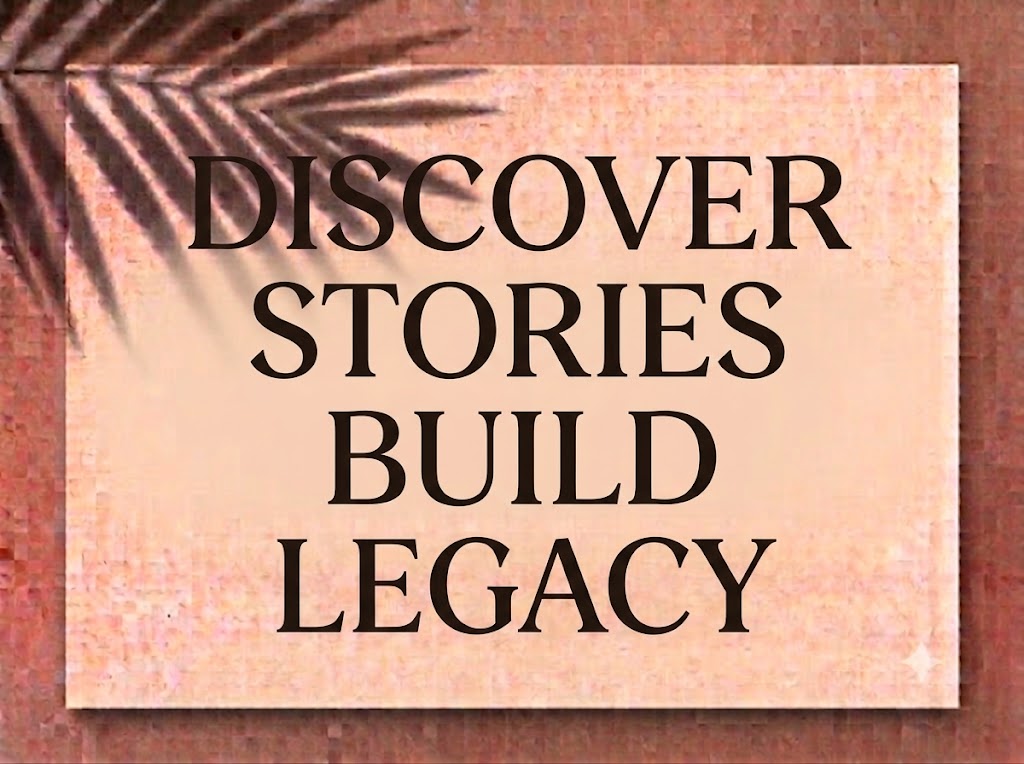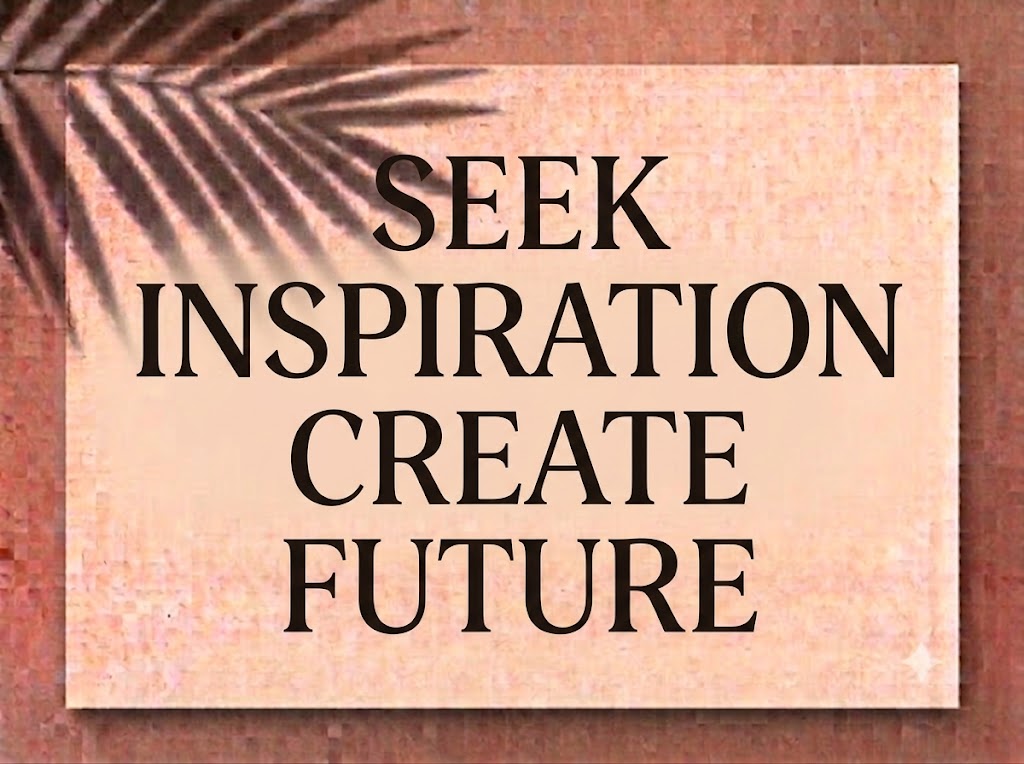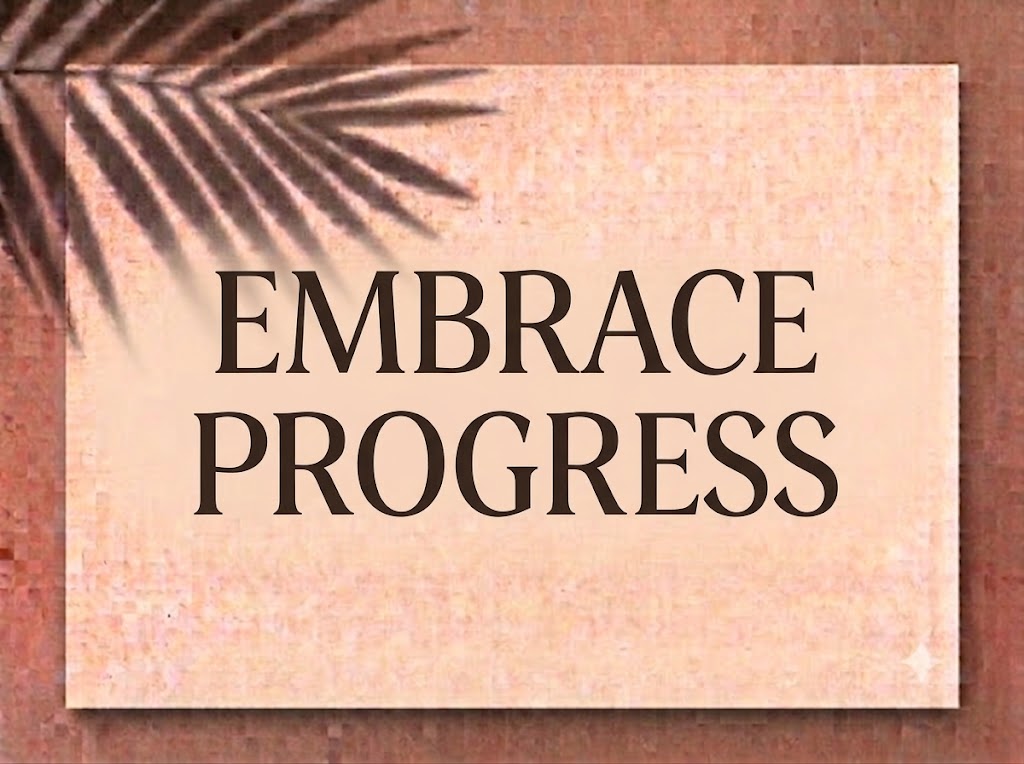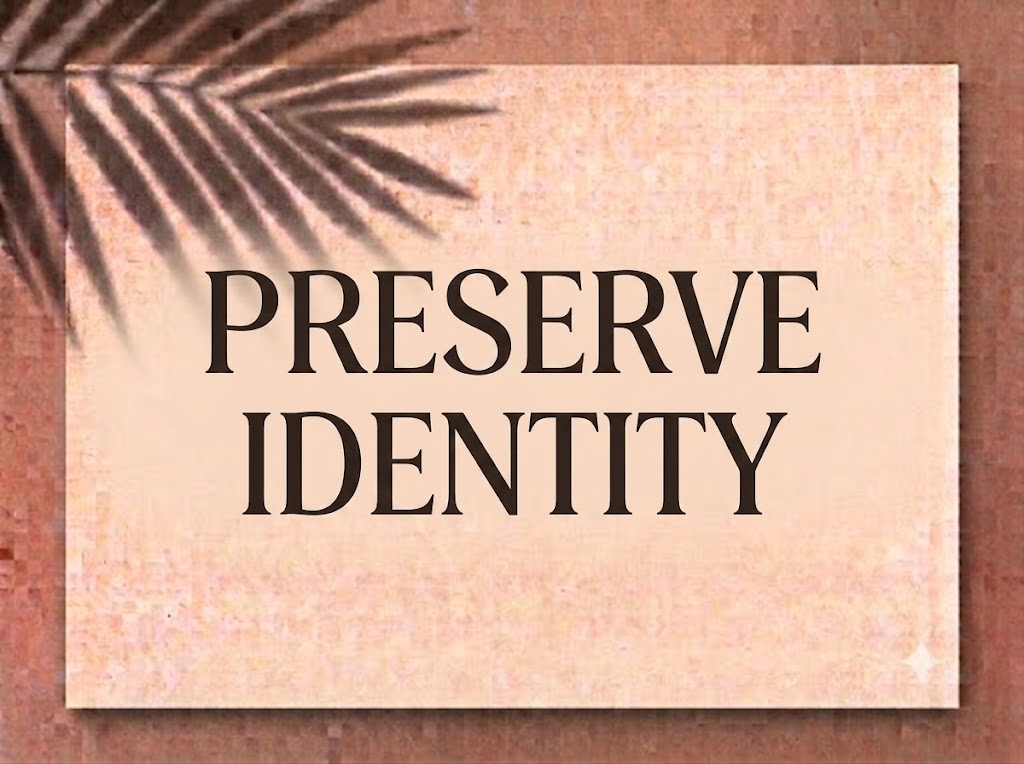
1FTV VIP Alverich
Trong ngành thiết kế đồ họa cao cấp, thời trang và sản xuất nội dung số, việc lựa chọn một phông chữ Serif vừa giữ được vẻ kiêu sa cổ điển vừa mang đường nét hiện đại là yếu tố quyết định giá trị thị giác. Một dòng tiêu đề được tạo hình tinh tế sẽ ngay lập tục nâng tầm đẳng cấp thương hiệu và thu hút sự chú ý của người xem.
Nếu bạn đang tìm kiếm một phông chữ hiển thị sang trọng, sở hữu các chi tiết biến điệu nghệ thuật cho bìa tạp chí, lookbook hay tiêu đề video ngắn, font 1FTV VIP Alverich chính là giải pháp lý tưởng.
Giới thiệu về font 1FTV VIP Alverich
Font 1FTV VIP Alverich là bộ chữ hiển thị có chân (serif display) mang phong cách tân cổ điển thời thượng, nổi bật với sự kết hợp giữa nét chữ Serif vững chãi và các đường nét cách điệu độc đáo:
Tên phông chữ: 1FTV VIP Alverich
Đặc điểm nổi bật của phong cách thiết kế VIP Alverich
Sức hút thị giác của font 1FTV VIP Alverich đến từ sự cân bằng giữa cấu trúc chuẩn mực và nét chấm phá nghệ thuật:
Nét tương phản thanh đậm tinh tế: Sự chênh lệch giữa các nét dọc dày dặn và nét ngang thanh mảnh mang lại chiều sâu nghệ thuật.
Chi tiết biến điệu ký tự độc đáo: Điểm đắt giá của phông chữ nằm ở các đường nét tạo hình phá cách nhẹ nhàng ở một số ký tự như chữ e với nét gạch nghiêng lạ mắt\.
Khoảng cách giữa các chữ (kerning) và độ giãn dòng được tính toán chuẩn xác, giúp các ký tự khi đứng cạnh nhau không bị dính nét hay rối mắt.
Tích hợp trọn vẹn bộ chữ cái hoa – thường, dãy chữ số 0-9 dáng đứng thanh lịch cùng hệ thống ký tự đặc biệt, dấu câu thông dụng.
Hình ảnh demo thực tế của font 1FTV VIP Alverich
Khả năng hiển thị của phông chữ này được tối ưu rất tốt trên nhiều tỷ lệ kích thước khác nhau:
Kích thước nhỏ (12pt – 24pt): Cấu trúc chữ đứng ngay ngắn và khoảng hở nội tại rõ ràng giúp bộ chữ thường và dãy số vẫn hiển thị sắc nét.
Kích thước lớn (36pt – 72pt): Đây là đất diễn lý tưởng nhất để 1FTV VIP Alverich phô diễn toàn bộ sự kiêu sa.
Ứng dụng trong thiết kế đồ họa và làm video
Sở hữu nét cá tính sang trọng và đầy tính nghệ thuật, font 1FTV VIP Alverich mở ra không gian ứng dụng phong phú:
Video ngắn (TikTok, Reels, Shorts): Phông chữ serif dáng kiêu kỳ này hiển thị rất đẹp trên khung hình đứng tỷ lệ 9:16. Nó cực kỳ ăn nhập với các video vlog phong cách sống.
Ảnh thu nhỏ YouTube (Thumbnail): Lựa chọn tuyệt vời cho các kênh làm nội dung về âm nhạc lofi, acoustic, chữa lành hoặc review đồ hiệu nhờ giao diện chuyên nghiệp và thu hút.